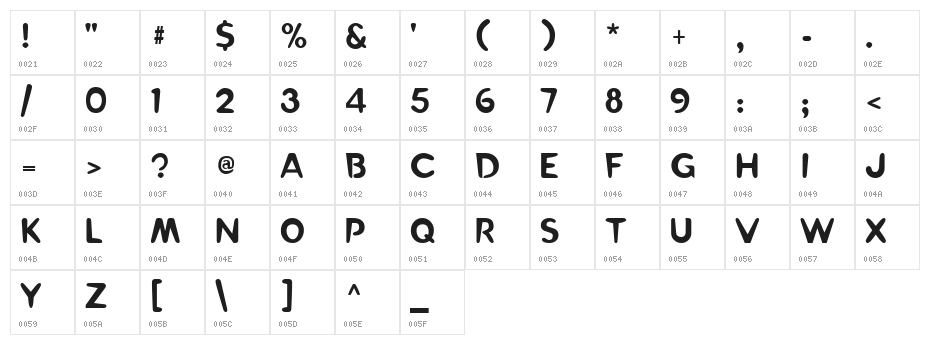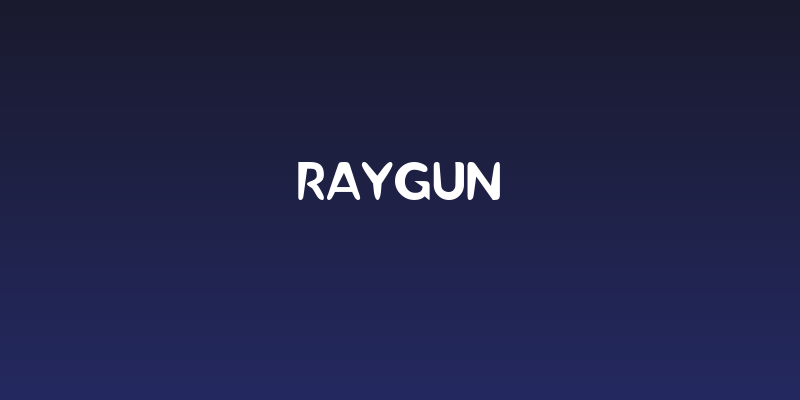
RayGun Font
| Estilo general | Playful |
| Proyectos propuestos | Ideal for children's books, playful branding, posters, and creative projects that require a fun and engaging typeface. |